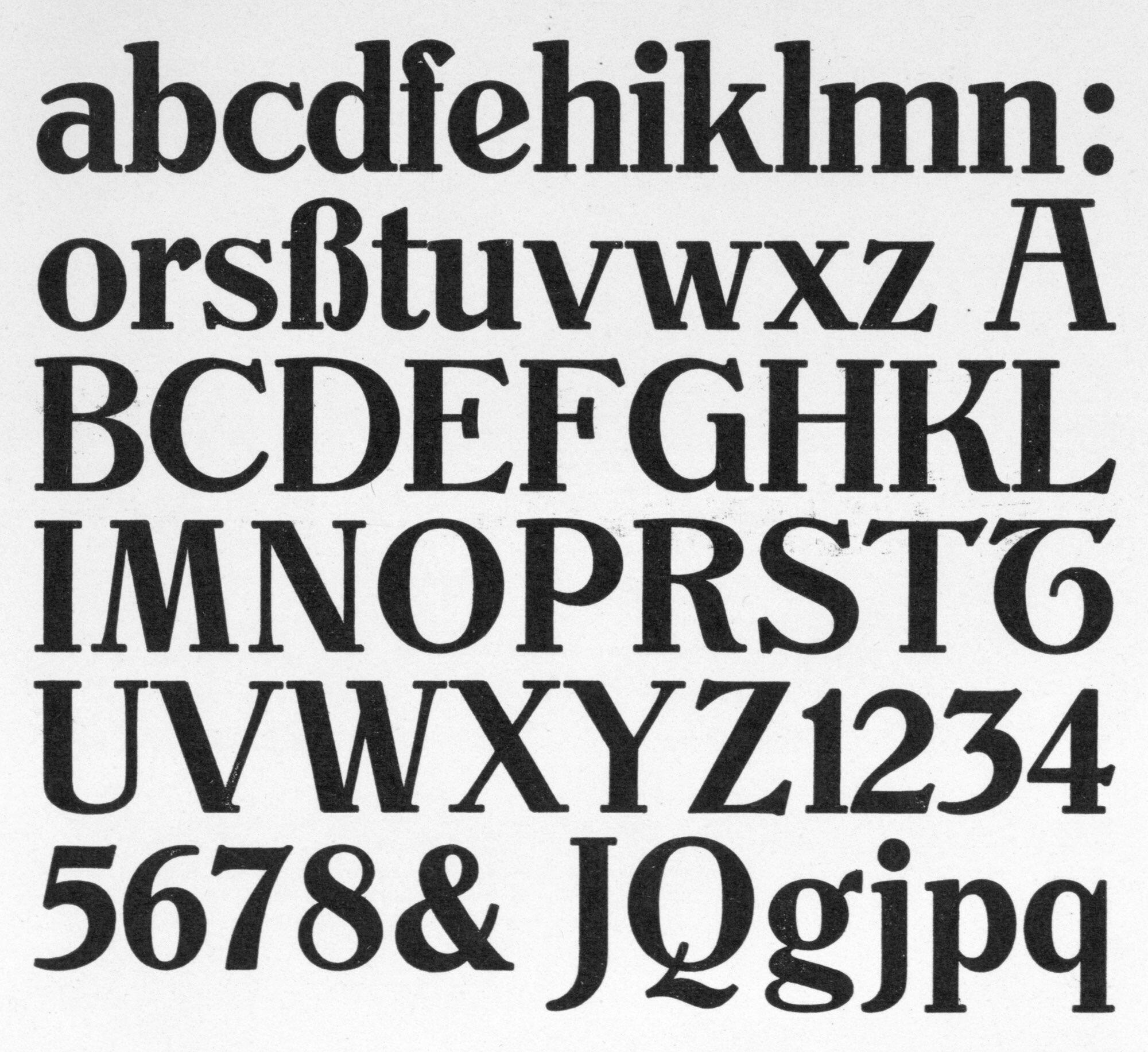
Font-Wiki: Augenheil-Antiqua
• 1907
• Serifen:
• serif
• Antiqua humanistisch
Die Augenheil-Antiqua von Richard Ludwig erschien Anfang des 20. Jahrhunderts. Die Schrift erschien in verschiedenen, mit Buchstaben (A bis D) bezeichneten Weiten, drei Strichstärken, zwei Kursiven und einem zusätzlichen engen Schnitt. In der Summe waren es schlussendlich neun Garnituren.